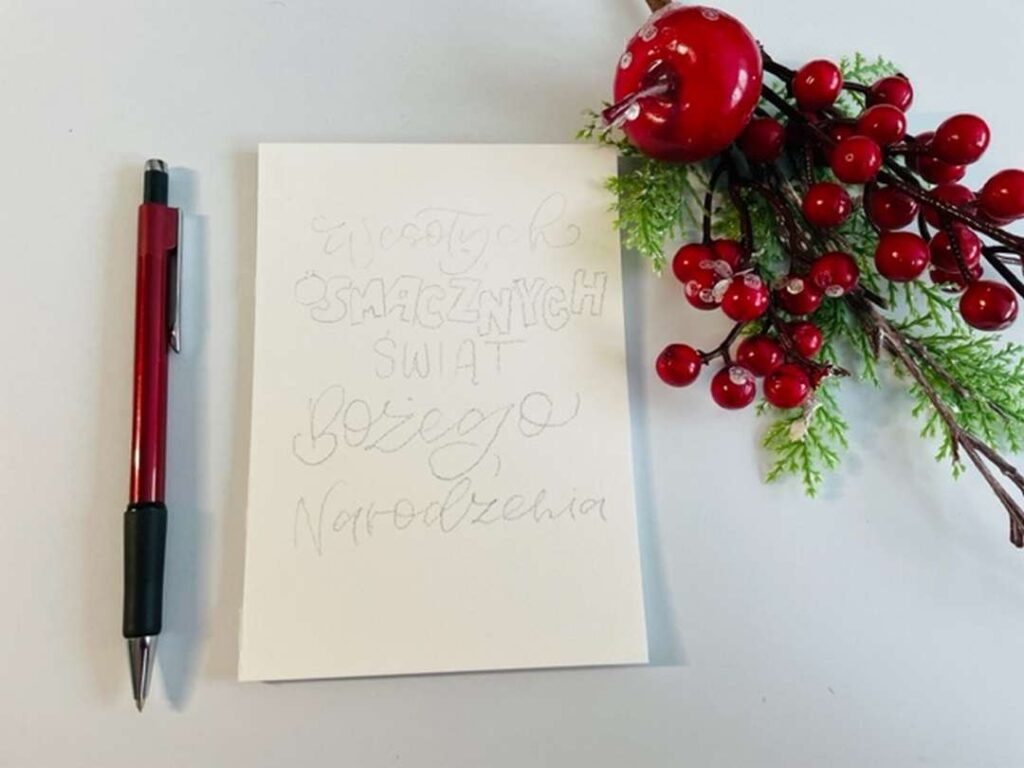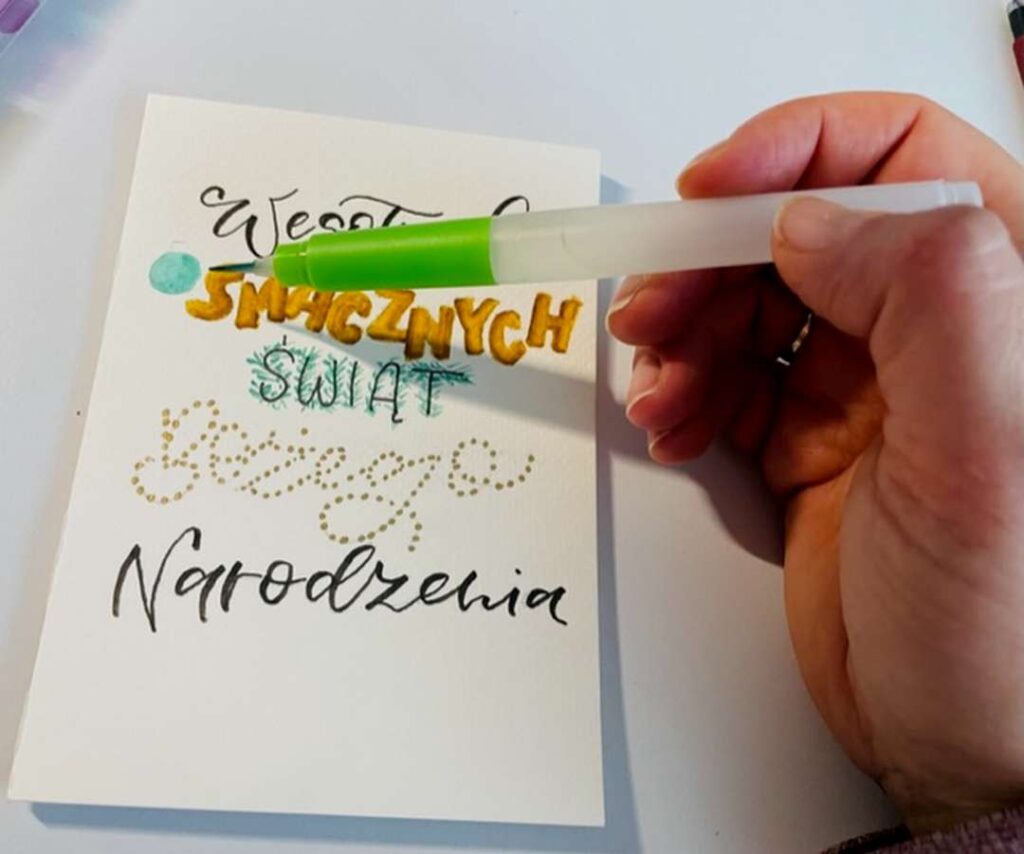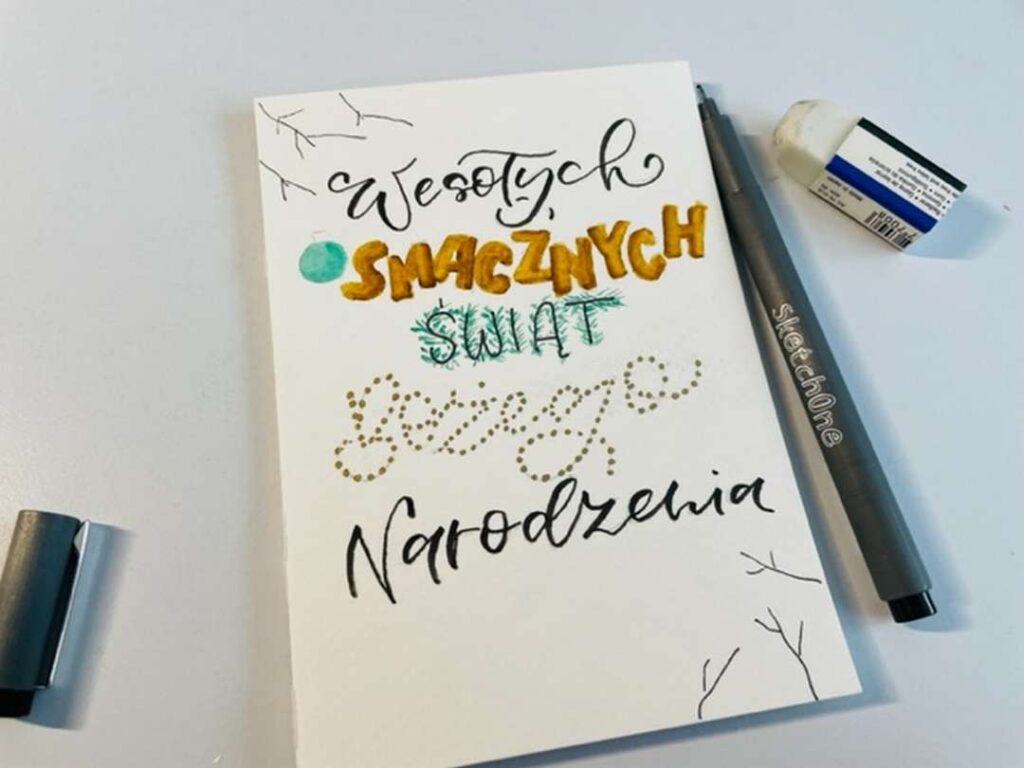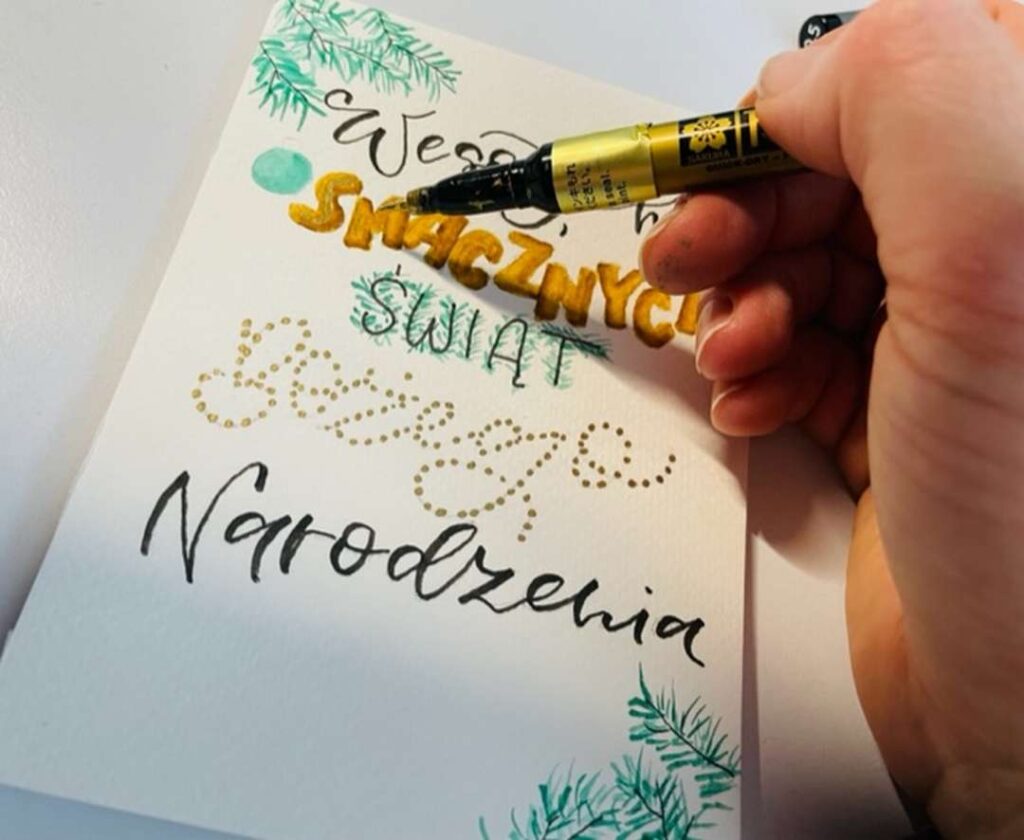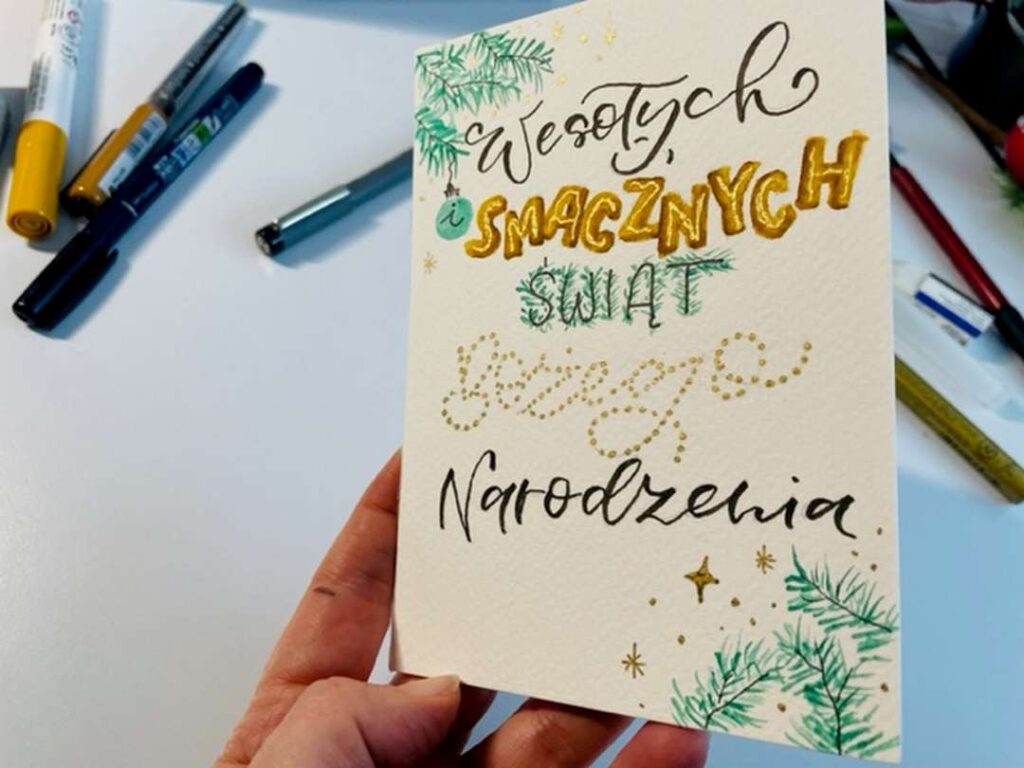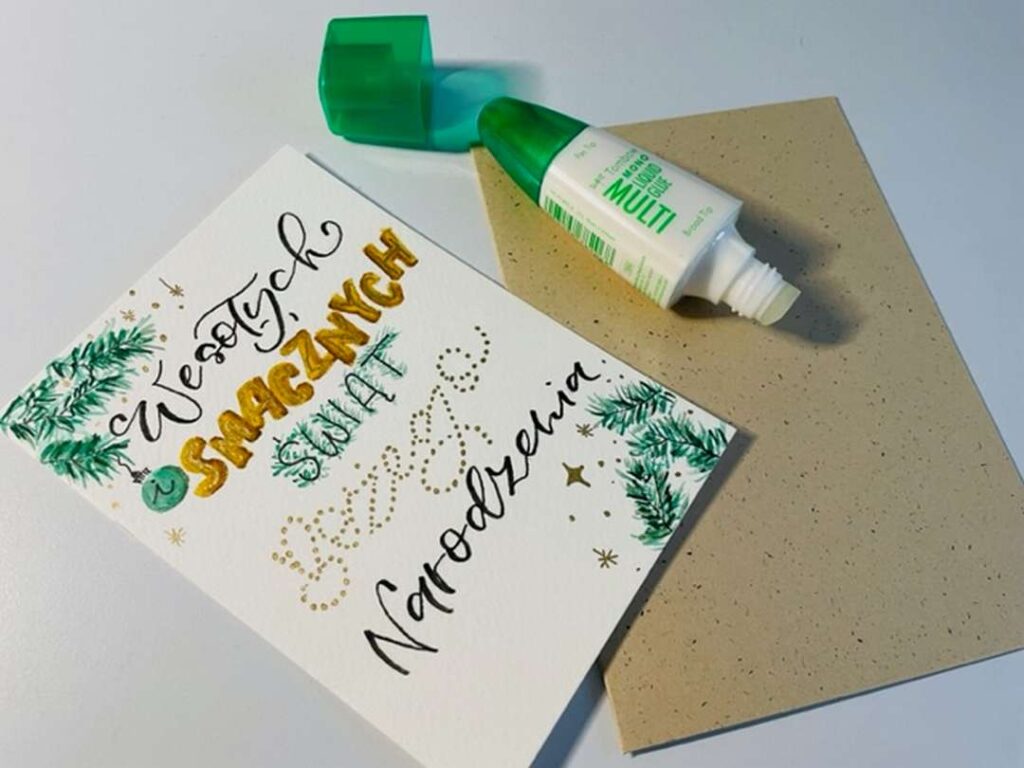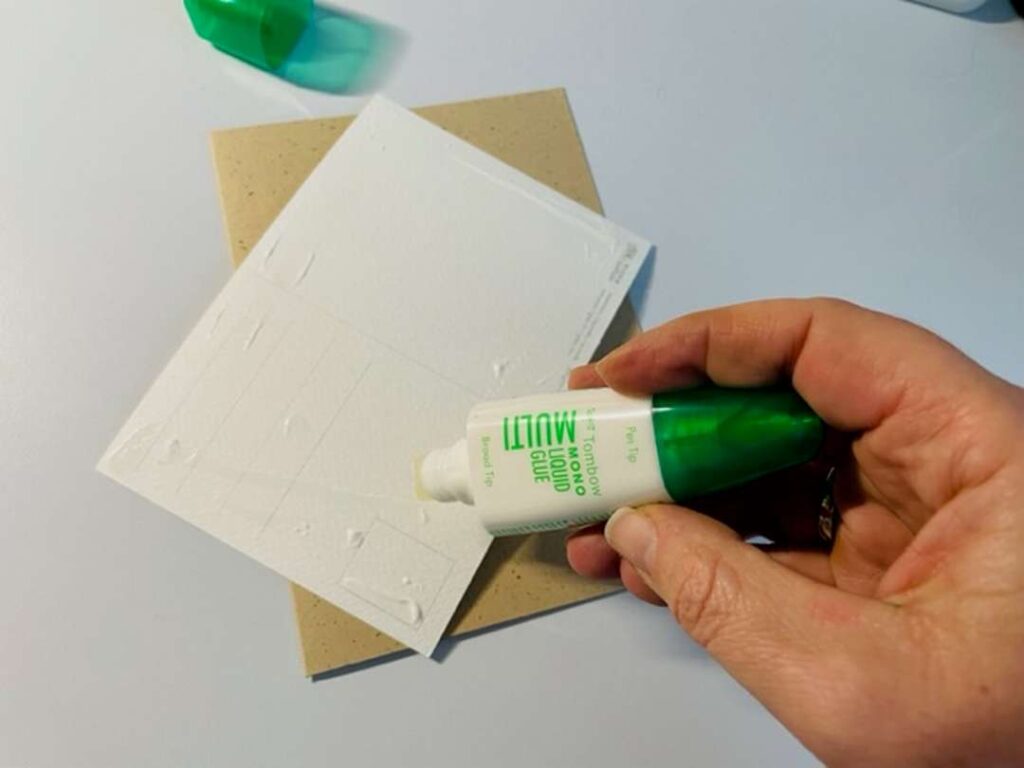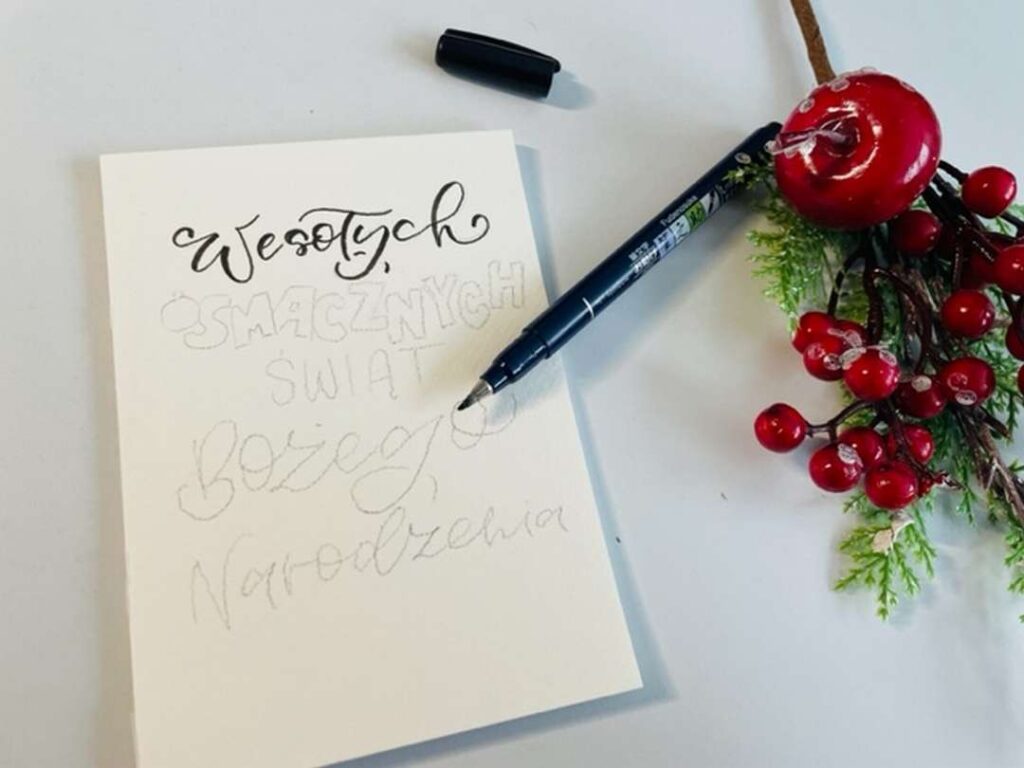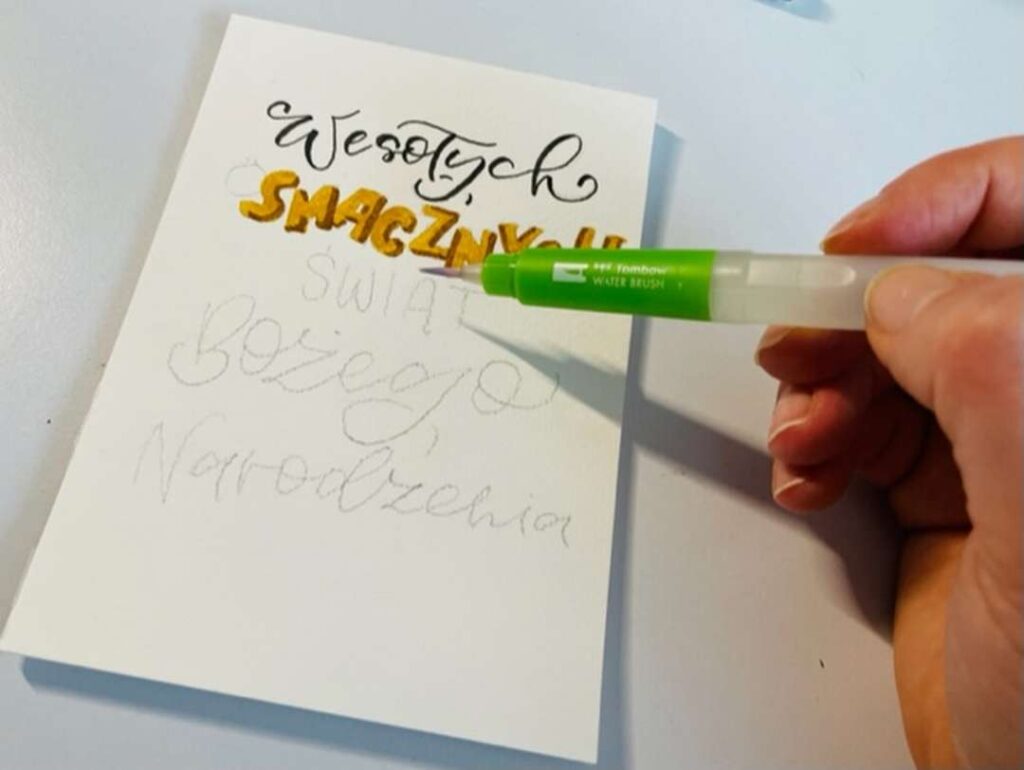
Lettering na Boże Narodzenie
Tworzenie letteringu na Boże Narodzenie może być zabawnym i twórczym zadaniem. W kilku krokach pokażę Ci jak stworzyć własny świąteczny lettering. Potrzebujesz do tego projektu brązowe i zielone brush peny, papier akwarelowy i kartkę oraz klej.
Materiały do wykonania letteringu na Boże Narodzenie
Aby wykonać projekt potrzebujesz:
• kartka, np. w kolorze brązowym
• papier akwarelowy
• gumka
• ołówek
• złoty cienkopis sakura (rozmiar S) lib inny dowolny złoty pisak
• pędzelek (np. ze zbiorniczkiem wodnym)
• dwa zielone brush peny (np. Karin Marker)
• dwa brązowe/ ciemnożółte brush peny ( np. ecoline)
• czarny brush pen (np. Fudenosuke)
• czarny cienkopis
• klej
Wykonaj szkic ołówkiem
W pierwszym kroku wykonaj szkic ołówkiem na akwarelowym papierze. Nie dociskaj zbyt mocno ołówka, aby później go łatwo wymazać.
Popraw pierwsze słowo brush penem
Czas na pracę z pierwszym brush penem. Polecam Ci Tombow Fudenosuke. Pracuj dokładnie i wolno, nie spiesz się.
Blendujemy litery
Wypełnij litery jaśniejszym kolorem (np. brązowy ecoline). Następnie ciemniejszym pisakiem dodaj cienie i kontury w literach. Na sam koniec wyblenduj pędzelkiem kolory. Pamiętaj, aby blendować całość, a nie sam brzegi- w przeciwnym wypadku pojawią się brzydkie zacieki.
Popraw słowo cienkopisem
Wybierz wodoodporny cienkopis i popraw nim słowo „świąt” .
Łańcuszek lampek w słowie
Wybierz złoty cienkpis (np.Sakura)
Wykropkuj słowo „Bożego” złotym cienkopisem.
Wykropkuj słowo „Bożego” złotym cienkopisem. Gdy cienkopis wyschnie – wymaż ołówek.
Dekorujemy litery zielonym kolorem
Nanieś zielony brush peny (lub dwa odcienie) na talerzyk lub folie i pobierz pigment pędzelkiem. Następnie w słowie „świąt” dorysuj delikatne igiełki. Wyblenduj bombke, w której umiścisz literę „i”.
Dekorujemy projekt
Czas na ostatnie dekoracje. Narysuj cienkopisem w lewym i prawym rogu gałązki choinki, a następnie pędzelkiem nanieś zielone igiełki.
Złotym pisakiem nanieś kreski w słowie „smacznych” – będą się ładnie błyszczeć (jak pierniczki).
Naklej projekt na kartkę
Posmaruj papier akwarelowy klejem i naklej na brązową kartkę.
Voila! Gotowe!